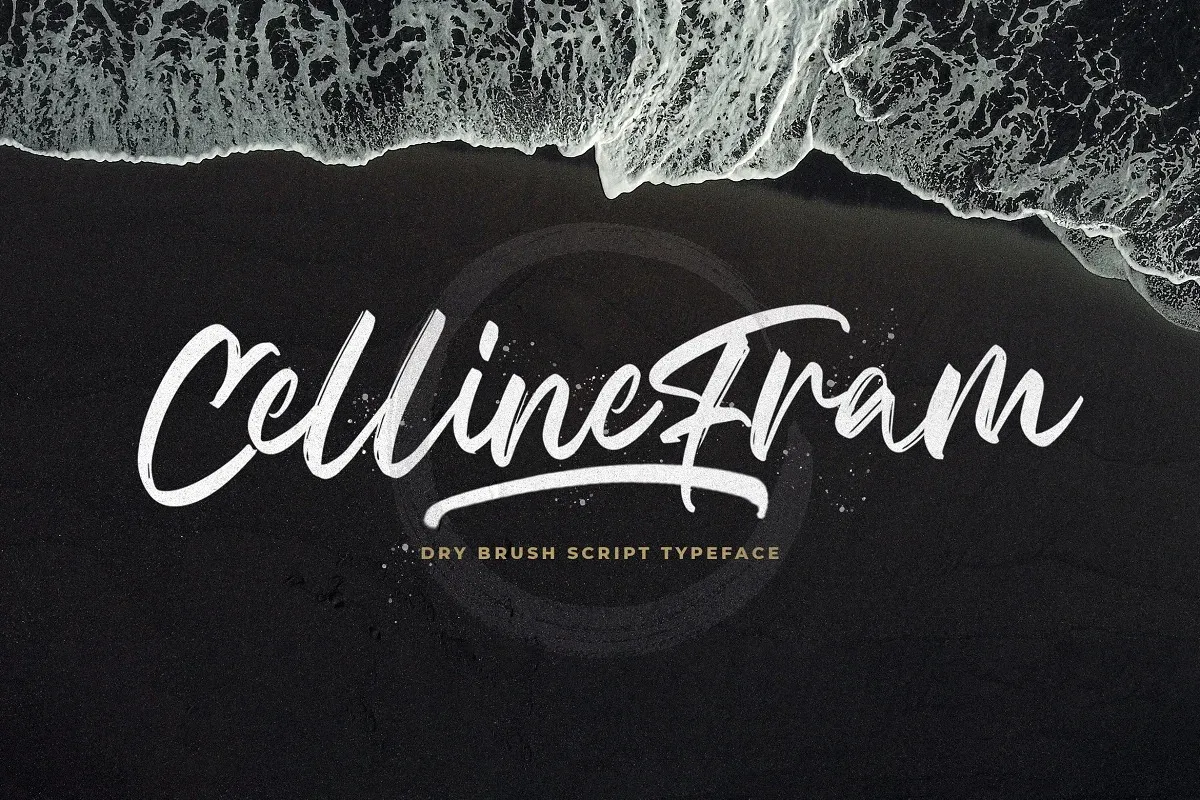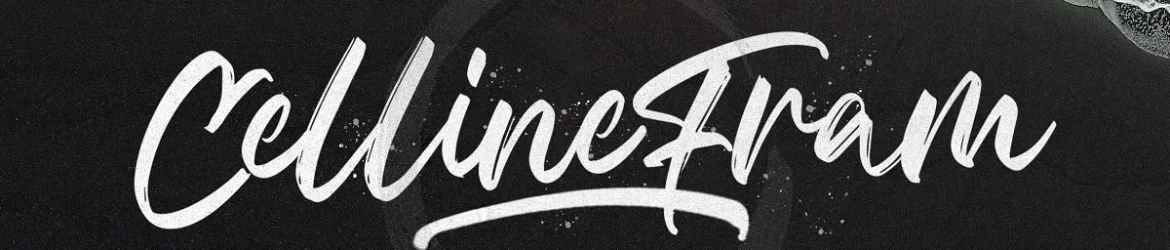
Celline Fram Font – Download Grátis
Esta é uma tipografia feita à mão com textura e uso de ferramenta artesanal, criada usando um método contemporâneo para design. A Amithen não possui uma linha base regular e foi feita manualmente, oferecendo um toque natural e irregular. Ela se destaca por seu caráter próprio que a torna ideal tanto para aplicação em displays quanto para designs decorativos. Ideal para aqueles buscando algo único e vibrante para suas projeções digitais ou projetos gráficos, a Amithen é uma escolha perfeita para quem busca um estilo autêntico e elegante. Esta fonte tem o poder de transformar qualquer design em algo especial, seja através da sua textura única ou do seu toque naturalmente irregular. É adequada para diversos tipos de projetos que exigem um toque personalizado e vibrante.